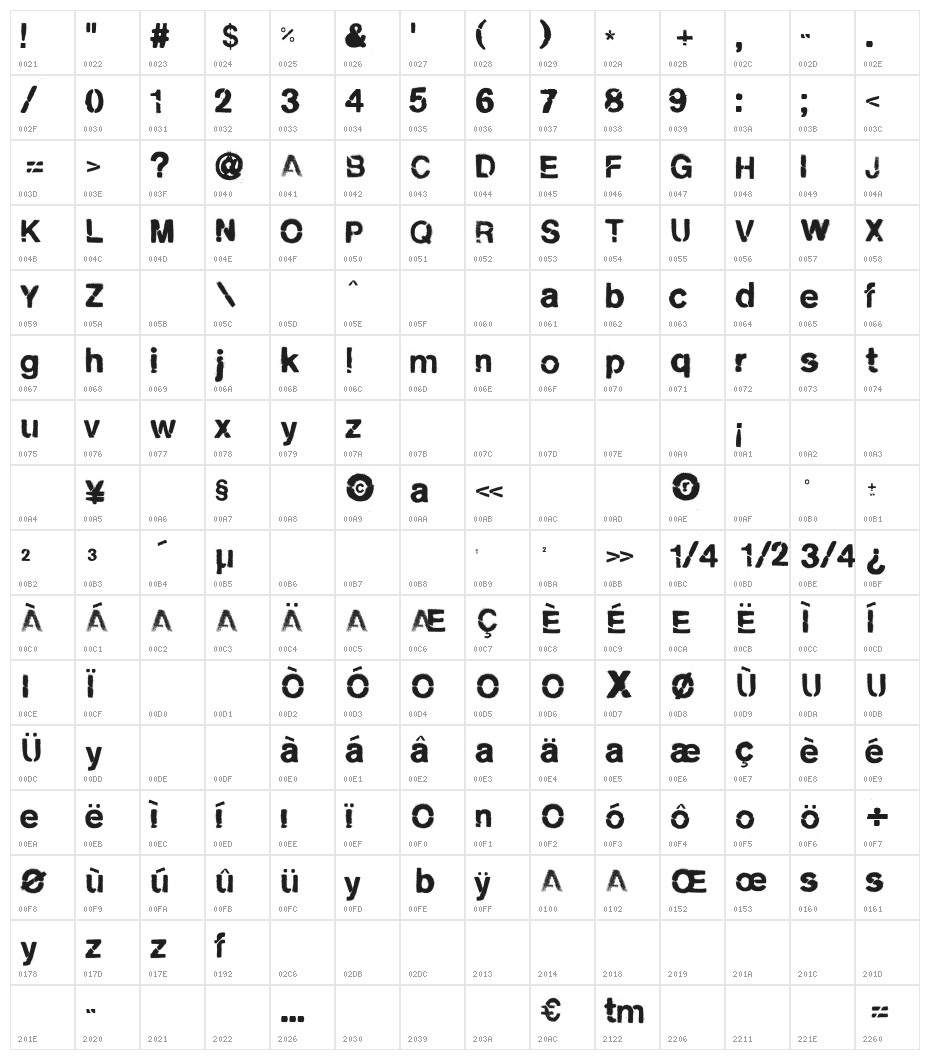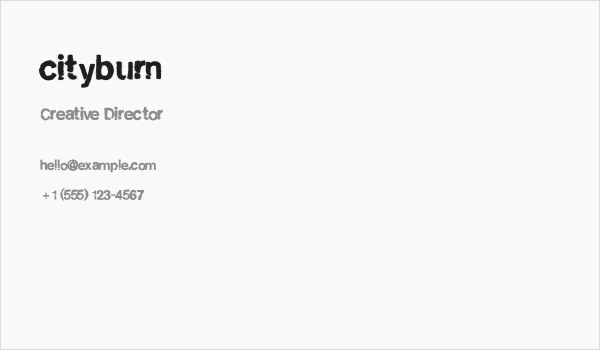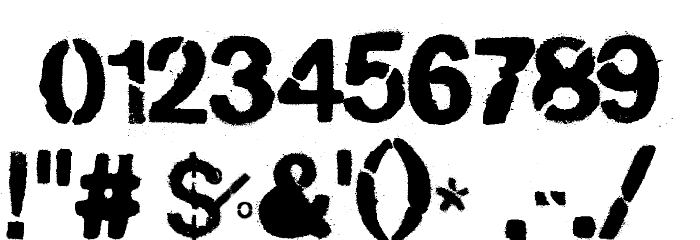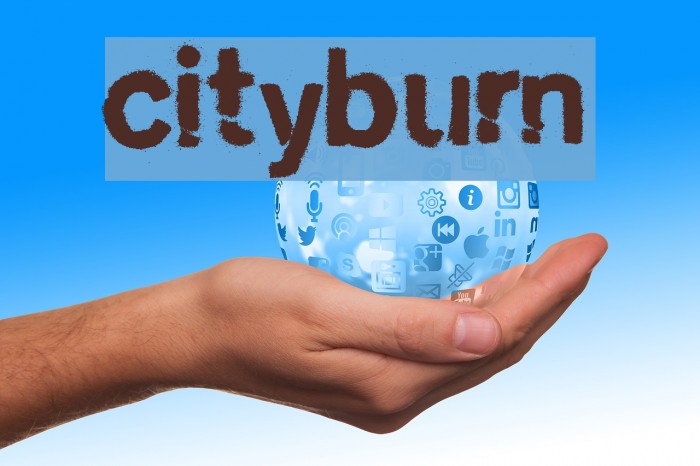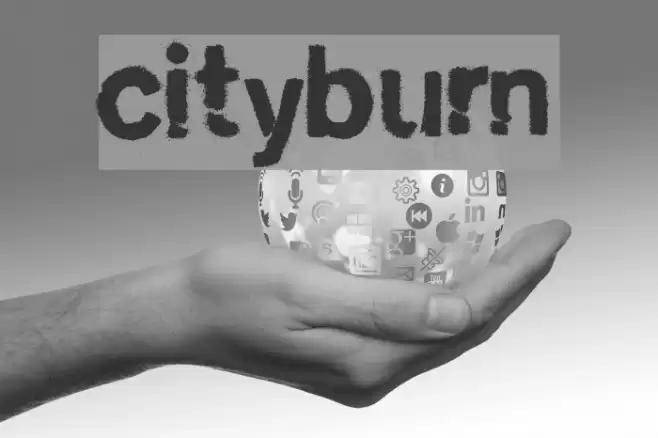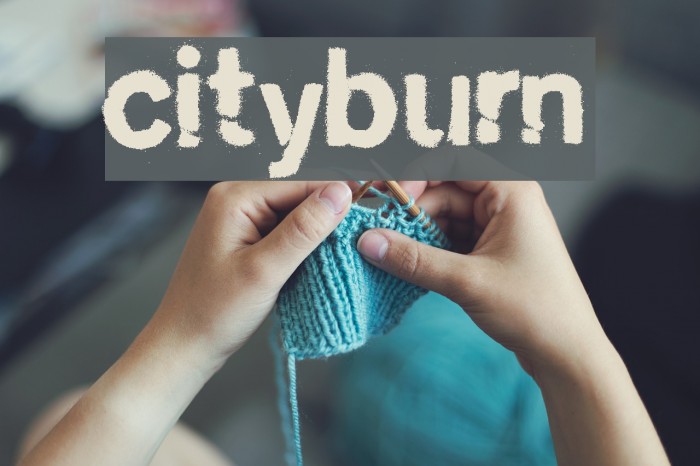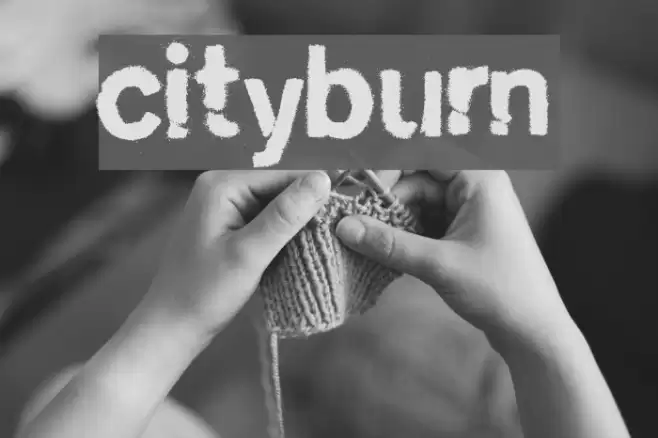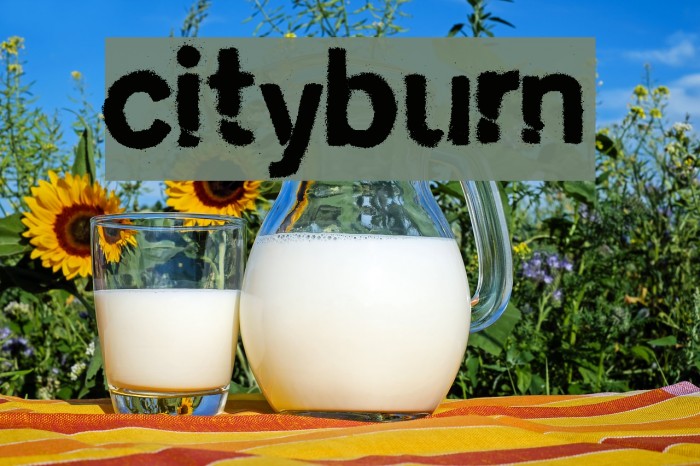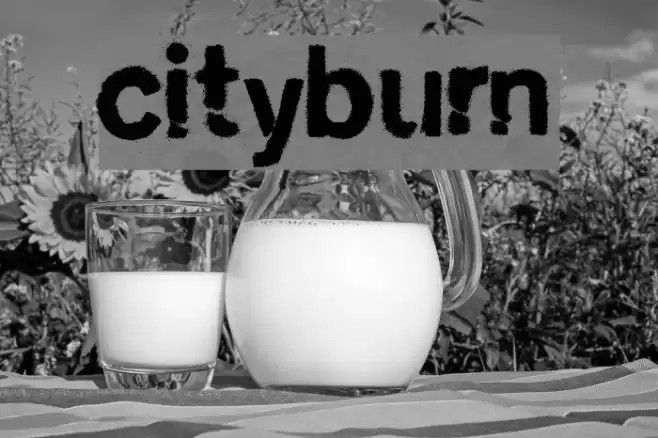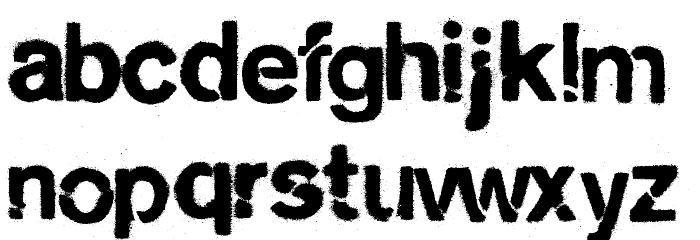
cityburn Font
✎ Distorted Eroded
| Style général | Urban, Industrial, Bold |
| Projets proposés | Ideal for street art, urban-themed posters, album covers, and branding that requires a bold, gritty aesthetic. |